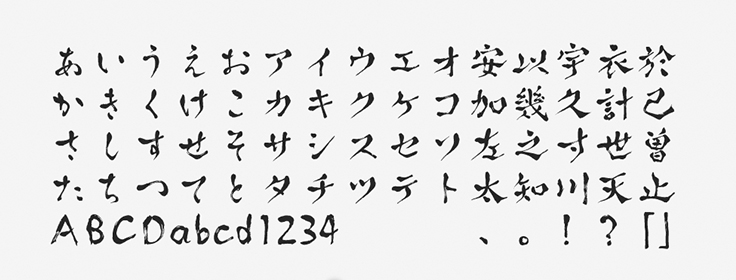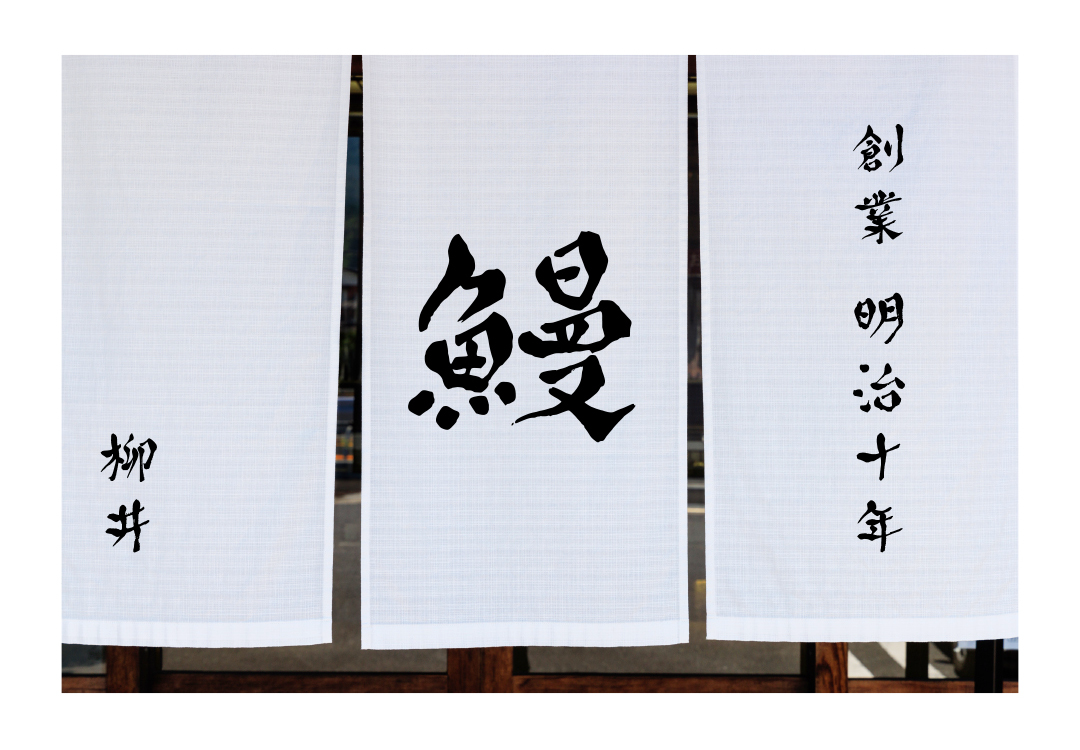
「うたよみ」について
うたよみは2016年の新書体として提供が開始されました。筆文字系のデザインフォントで、書家による毛筆の文字をもとに設計されています。横画には波打つような隷書の波磔(はたく)のような勢いがありますが、縦画では緩やかなカーブが描かれています。
「うたよみ」の特徴
縦画と横画の特徴の違いにより、静と動が入り混じったような独特な雰囲気を感じさせます。手書きならではの温もりもあるフォントです。字面の大きさや画線の太さをはじめ、線のかすれなども含めて「あえて整えすぎない」デザインが追求されています。
うたよみは特に縦組みで最適なバランスとなるように設計されているため、原則として推奨されるのは縦組みでの使用です。整いすぎていないフォントですが、個々の文字を組んだときの見え方には配慮されており、重心が細かく調整されています。
私はフォントを「声色」にたとえて説明することも多いのですが、手書き系や筆文字系のフォントでは特に書風に注目すると特徴をつかみやすいです。「その文字から感じ取れる声はどんな声なのか」を想像しながら選ぶと良いですね。うたよみは、手描きテイストが強くて整いすぎていないことが魅力です。
タイトル・見出し、雑誌、商品パッケージ、チラシ、看板、暖簾
「うたよみ」の書体情報